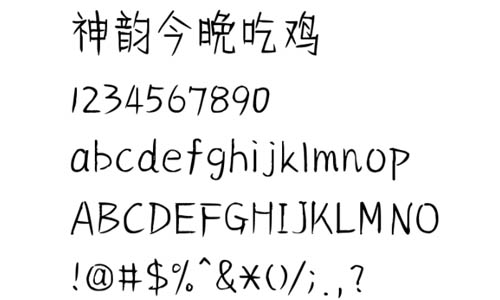
神韻今晚吃雞字體是由神韻字庫(kù)推出的一款手寫字體,“大吉大利,今晚吃雞”喜歡玩網(wǎng)絡(luò)游戲的小伙伴們對(duì)這句話不陌生吧,對(duì),它來(lái)自《絕地求生:大逃殺》。這款字體筆畫犀利、剛猛、鋒芒畢露,與槍戰(zhàn)游戲非常吻合。字體筆畫清晰易讀,閱覽流暢,久讀不膩,歡迎喜歡的朋友前來(lái)下載。